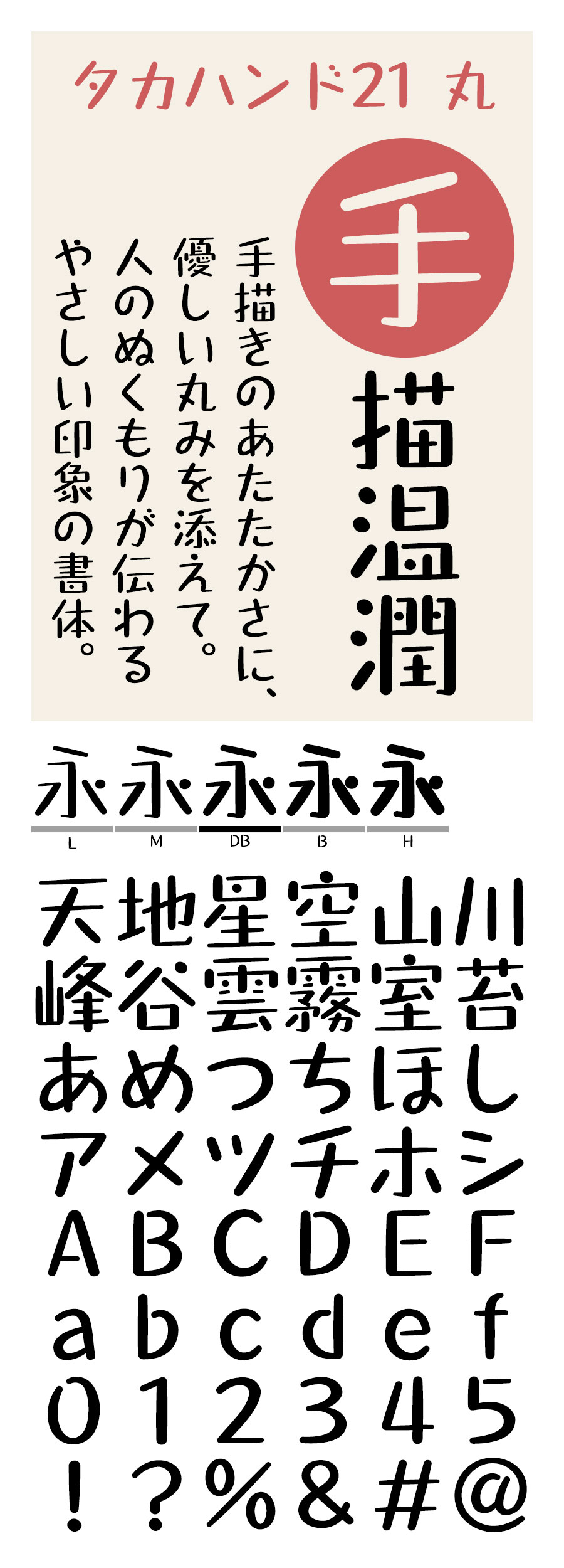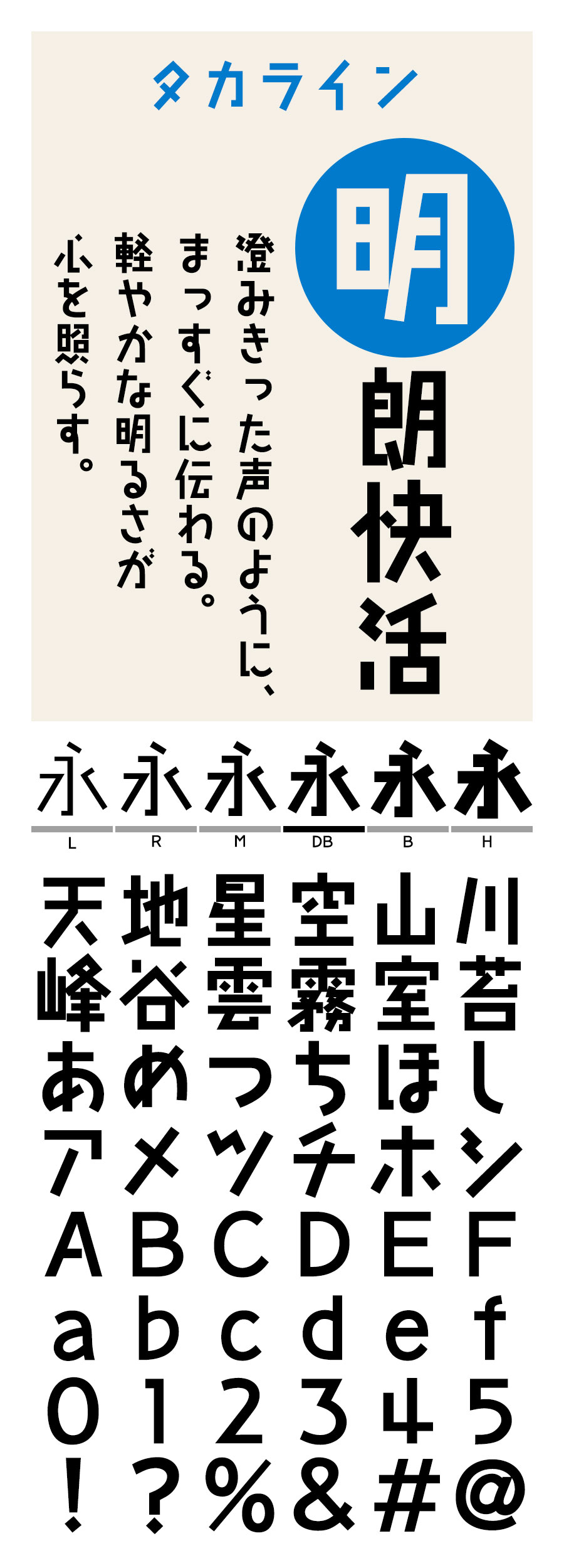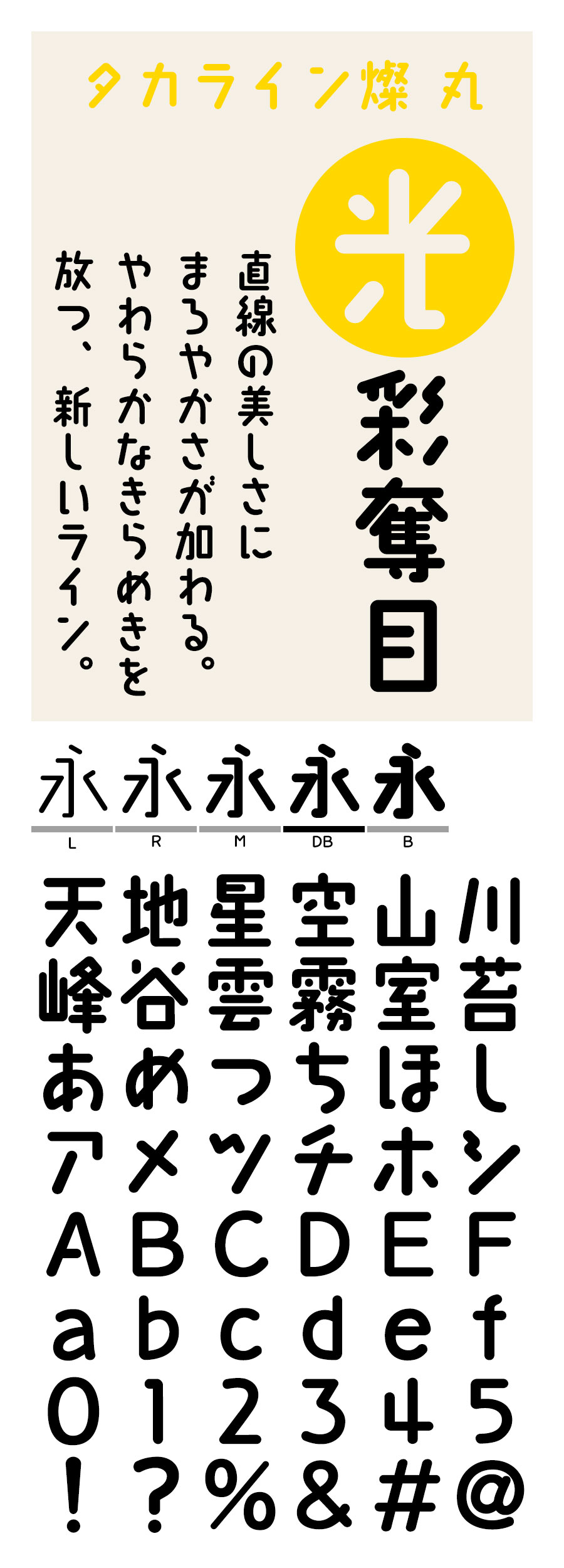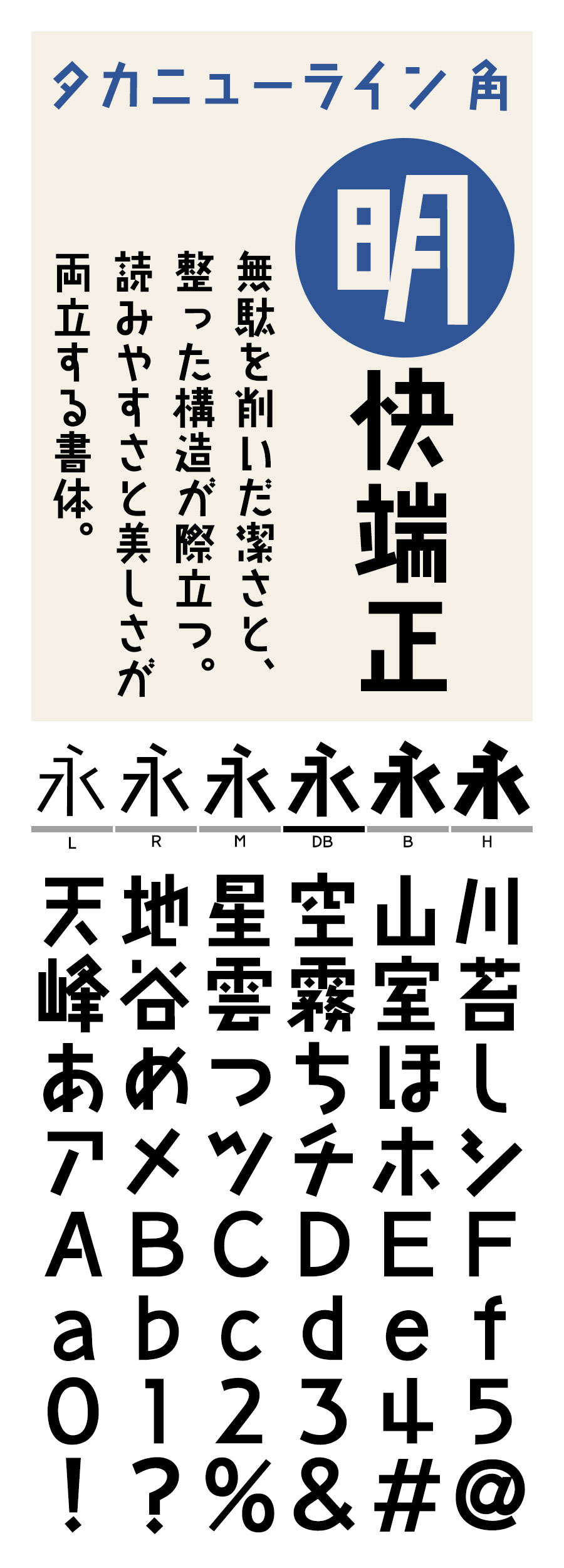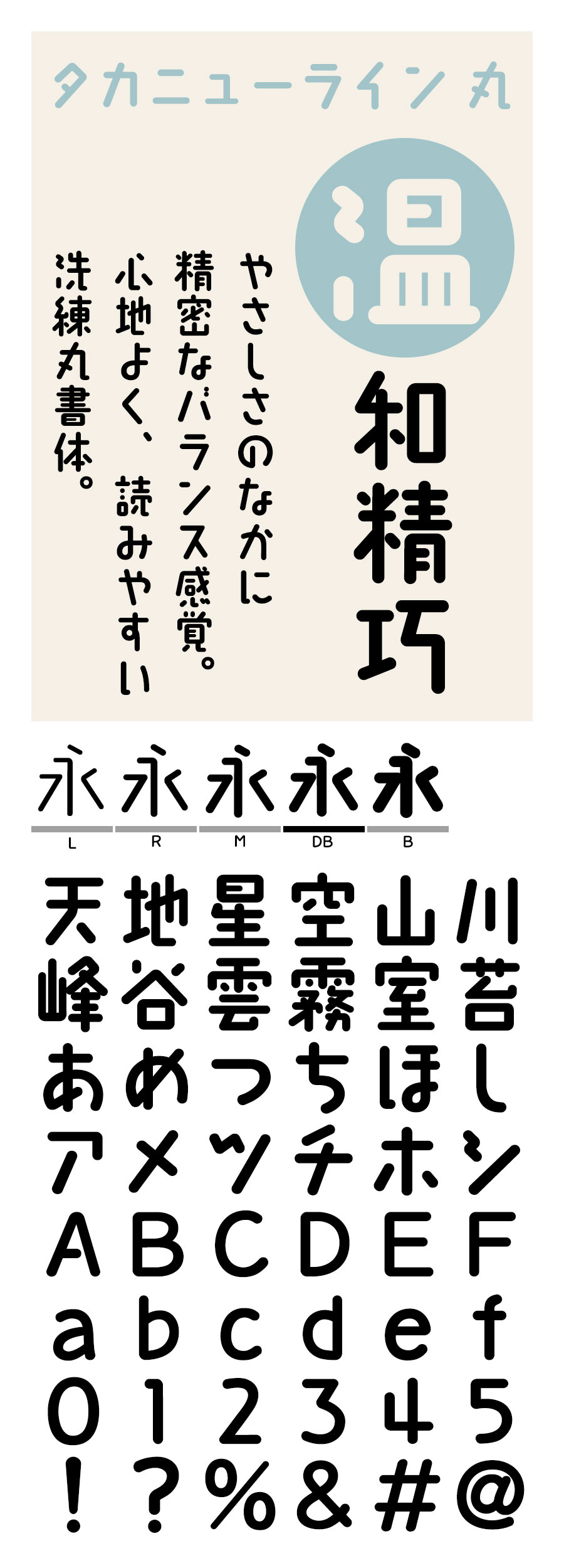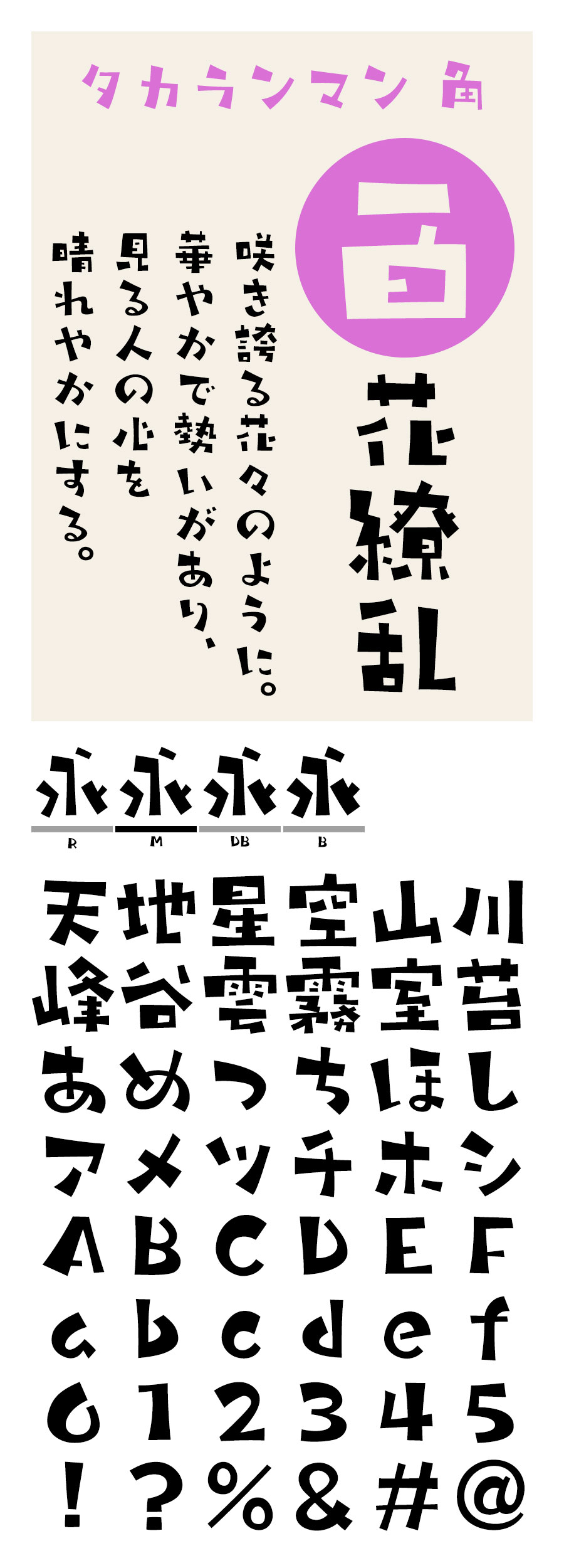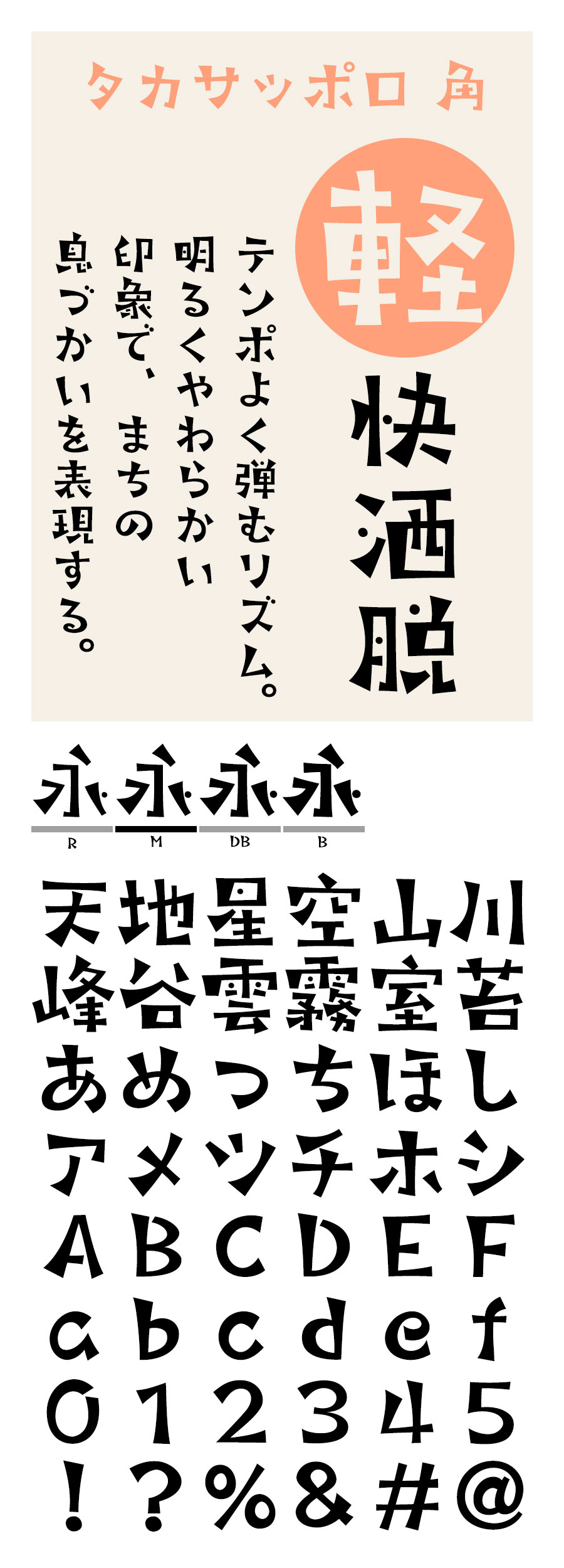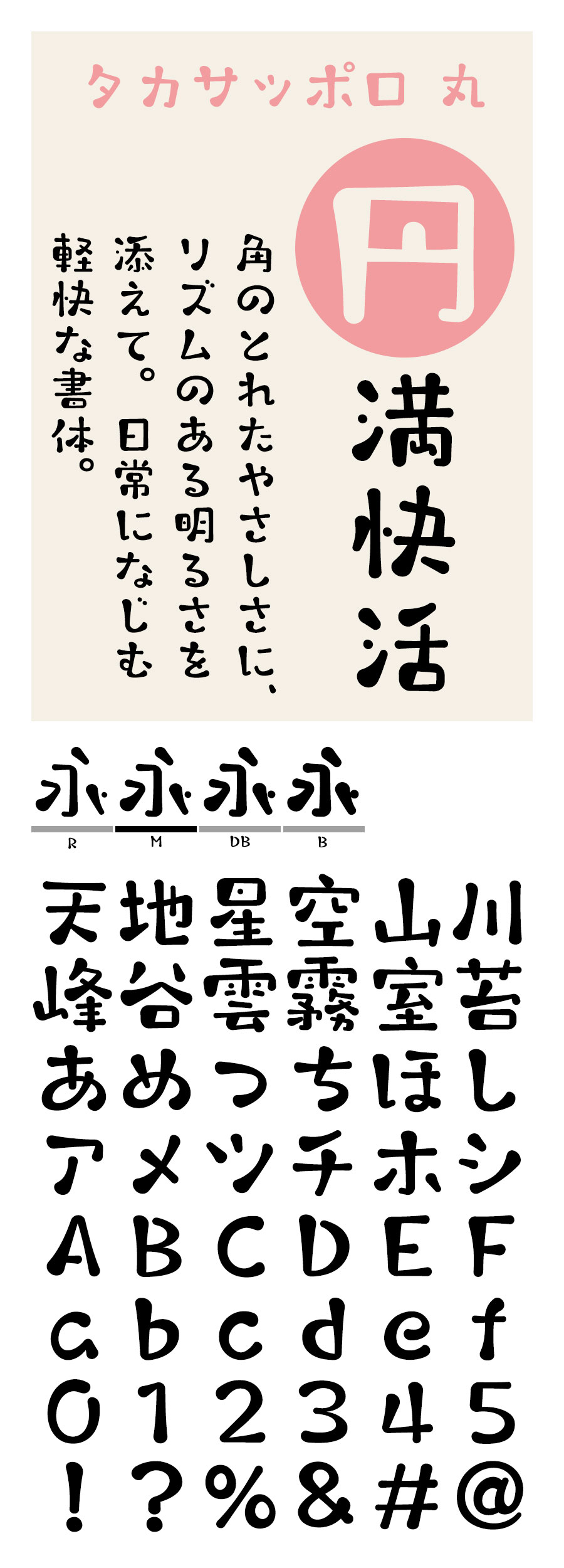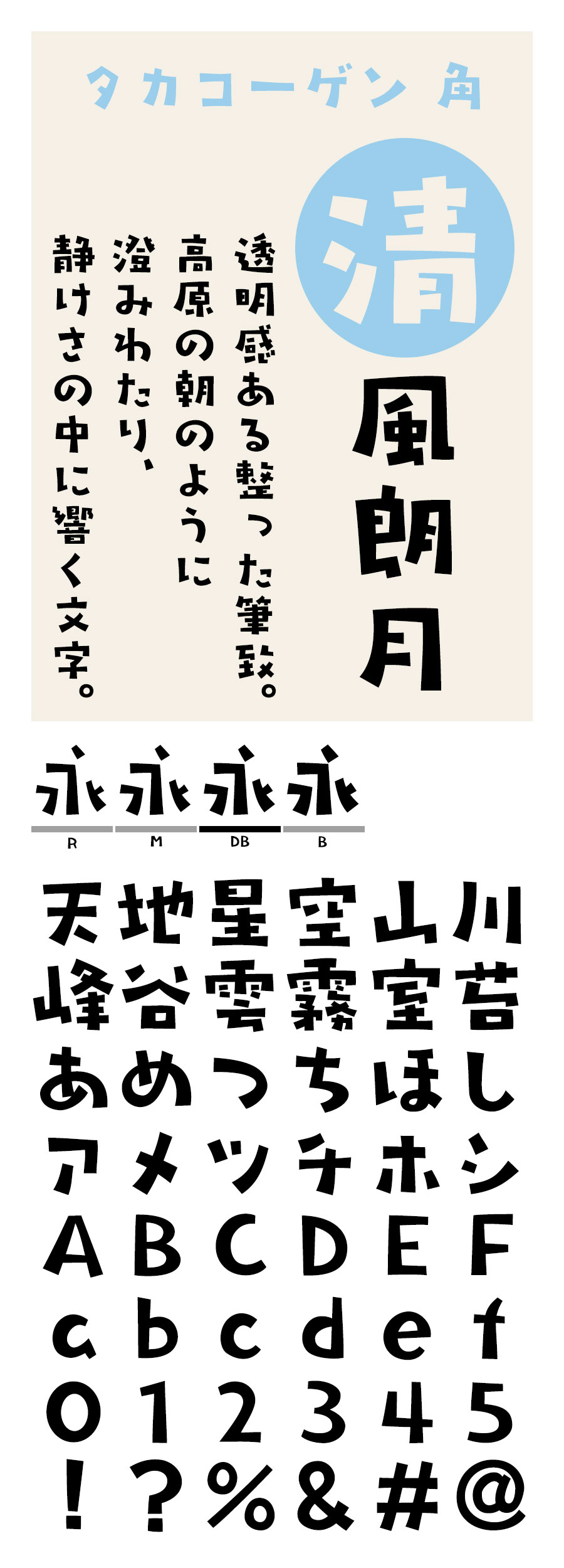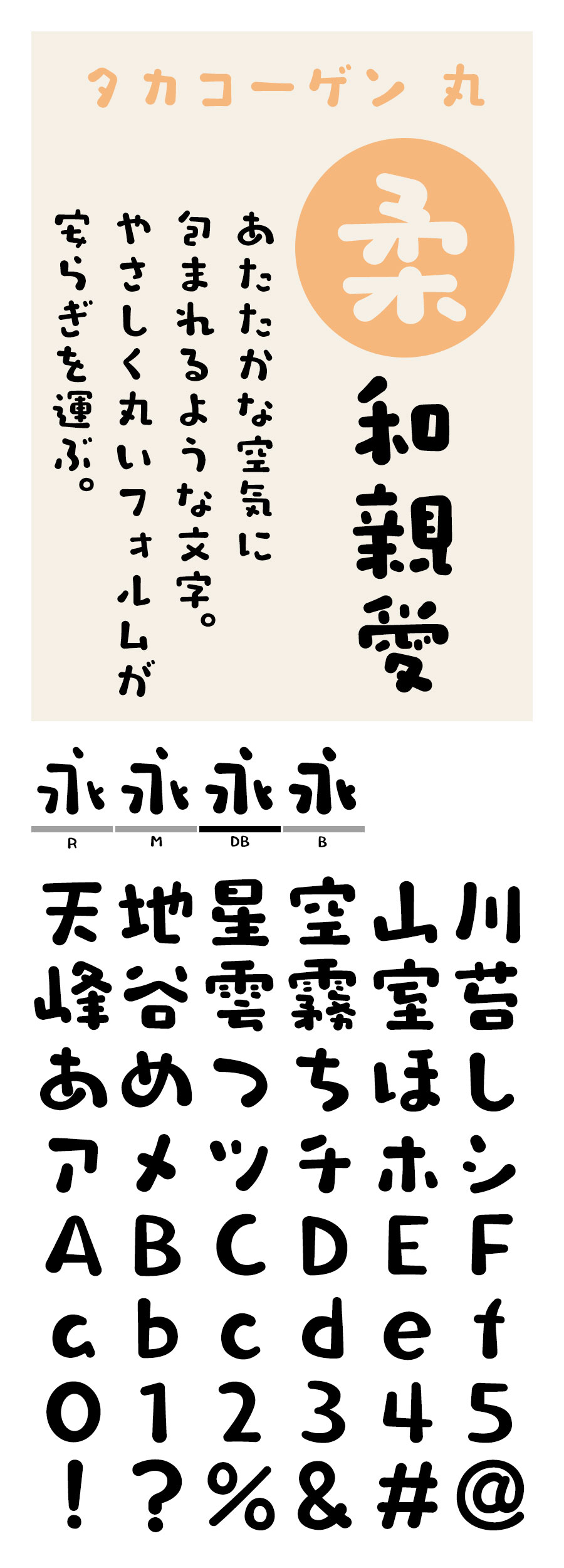
手書き風のやさしさと確かなデザイン性を備えたタカ書体は、今、誰もが使いやすい“プロの道具”として再スタートを切ります。
タカ書体とは ―― タカ書体・高原さんの軌跡
タカ書体──書体作家・高原新一が描く文字の世界。
タカ書体は、タイプ作家・高原新一氏が手がける、手書き風の温かみと親しみやすさを大切にした日本語フォントブランドです。
1987年、モリサワ社から発表された写植書体「タカハンド」にはじまり、以降30年以上にわたり、手書きの感触や柔らかなフォルムを活かした書体づくりを続けてきました。現在では50種を超える書体が、広告・出版・映像・Webなど幅広い領域で活用され、日本タイポグラフィ年鑑グランプリやニューヨークTDC展入選など、数々の賞も受賞しています。
文字に人生を賭けて――タカ書体・高原さんの軌跡
タカ書体 80年代の印刷出版業界誌に掲載される高原さん
<80年代の印刷出版業界誌に掲載される高原さん>
独学のレタリングから現場修行、そして書体の誕生と事業化へ。今回のインタビューでは、高原さんに原点、上京時代の修行、コンテスト挑戦の裏側、そして自社ブランド立ち上げに至る決断までを伺いました。
原点 — 文字に触れた最初の手応え
タカ書体 中学1年生当時に書いた漫画の模写
<中学1年生当時に書いた漫画の模写>
幼少期の模写と独学のレタリングが、のちの設計思想と観察眼を育てました。実作の成功体験が「文字を作る喜び」を確かな実感に変えていきます。
生来絵を描くのが好きで、小学生時代は皆が弁当食べてる時に、私は漫画等を自分なりにアレンジ、短縮版にした手製の紙芝居を何度か披露したものです。今でも覚えているのは“柔道の父、嘉納治五郎”です。
小学6年生あたりから、漫画の模写を夢中でやってましたが、今考える現在の文字作り土台にもなっている気がします。また中学時代、美術時間に作ったポスターが中学、高校部門で第1位となりこの辺りから、デザイナーになろうと決めました。
中学時代にはレタリングを学びたく、新聞の見出し等を切り抜き自分なりに教材らしきものを作ったりして、明朝体の漢字など1文字ずつレタリングしました。エレメントの基本みたいなものを少しは身につけ始めていた様です。
高校では3年生で『レタリング同好会』を発足。少しばかりの同好会予算で、レタリングの教材をいくつか購入しレタリングを楽しく学びました。メンバーと学校祭の立体の看板を制作。評判は最高で、先生からも大変に喜ばれました。
上京と修行と独立と挑戦 — “線”を極めて目標を定める
タカ書体 デザイン事務所で培った溝引きスキルを活かした21歳頃のレタリング
<デザイン事務所で培った溝引きスキルを活かした21歳頃のレタリング>
現場で叩き上げた版下スキルと“溝引き”の習熟が、カーブの感性を獲得。独立後はコンテスト挑戦を通じて「自分の書体を世に出す」明確な目標へ。
志望していた美大は経済事情で断念、単身上京します。入学金等を貯めるため埼玉の某工場でがむしゃらに働き、翌年には念願の日本デザインスクール(現日本デザイン専門学校)に入学。
縁があって銀座にあるデザイン会社に見習いとして働くことになり、学校は中退。主に版下作業でしたが毎日が楽しく、社長からは高原こうげんのゲンからとって、スピードのゲンちゃんと呼ばれました。そのとき道具で『溝引き』と言うのを知りました。この溝引きとは思い通りのカーブラインをキレイに引くことが出来るもので、浮世絵や美人画などの曲線を描くのにも用いられていたらしいです。そしてこれが後のあの『タカハンド』の微妙なカーブラインを自由自在に使いこなせる原点だったのです。
東京でのデザイン修行は5年間ときめていたので、北海道に戻り2年間札幌のデザイン会社の勤務し、目標通り25歳で独立します。自分には遠い世界と眺めるだけだった写研が開催していた『石井賞タイプフェイスコンテスト』に対して、これこそ挑戦しないとダメだ!と俄に意欲が湧きはじめ、この辺りからから私の大きな夢は、「自分の書体をいつの日か世に出したい」というものになりました。
第3回のコンテストに初出品するも入選出来ず、2年後の第4回のコンテストで初入選(27才)。以来、連続入選、複数点入選を続けるも目標の第1位は届かないでいました。
「タカハンド」誕生と夢の具現化 — 佳作から商品化、写植発売へ
タカ書体 タカハンドMの原字
<タカ書体 タカハンドMの原字>
受賞結果は“佳作”。それでも価値は作品そのものに宿る。逆転の電話から商品化が決まり、写植文字盤化で夢が形になります。
その頃、モリサワも同じくコンテスト開催します。1984年の『第1回モリサワ賞・国際タイプフェイスコンテスト』にディスプレイタイプ部門に出品。世界16ヶ国から202点の多くの作品が集まり、審査の結果、私の作品は佳作でした。その上に1位と2位がいるので商品化は絶対無理で、入選の喜びより佳作だったことに本当にがっかりしていました。
ところが後日かかってきた電話では、このコンテストの受賞作品の中で商品化したいのは、1位と2位のものではなく私の作品をと言うものでした。この作品が後の『タカハンド』になるのです。
その後制作に着手します。当時、私はデザイン事務所の仕事は一通り目を通しながらも、『タカハンド』の制作に集中しました。1997年完成した『タカハンドM』は写植文字盤化され発売。34才の時でした。最終的にファミリーは5書体になりました。
完成後には再びコンテストへのチャレンジを開始し、『石井賞タイプフェイスコンテスト』は第11、12、13回と入選・3位入賞、『モリサワ賞』は第2回は佳作入選、第3回は最高位の金賞不在の中、銀賞と審査員賞のW受賞を果たしました。
タカ書体 タカハンドM制作時の様子、6畳和室制作室にて
<タカハンドM制作時の様子、6畳和室制作室にて>
ロゴ・タイポアート — 書体とロゴ、教育・出版で広げた射程
タカ書体 デザイン業界紙に掲載された高原さんによる『CI』『VI』
<デザイン業界紙に掲載された高原さんによる『CI』『VI』>
タイプフェイスと並行して、ロゴ・シンボル、個展・海外展、教育・出版へと活動は拡張。社会への還元が次世代の眼差しを育てます。
28才時に大先輩に推薦いただき、日本タイポグラフィ協会の会員になります。
「タイプフェイス」はタイポグラフィの根っことも言えますが、シンボルマーク、ロゴタイプの世界もそうです。当時流行の『CI』『VI』の公募にも書体コンテストと同様、多くチャレンジ。30代がその全盛で、企業始め行政のお仕事も色々やらせてもらい、その多くは当時のロゴ・マーク集の刊行物に掲載されました。また『タイポアート』と称してタイポグラフィ作品を版画にし、個展を開いたり、タイポグラフィ協会のグループ展や海外展にも参加。その間、デザイン専門学校の非常勤講師として後輩の育成にも取り組みました。
20代の終わり頃に制作した絵文字をテーマにした本を30代半ばで自費出版し、漢字に少しでも関心を持って欲しいとの願いから北海道の全公立高校、札幌市内の全中学校に寄贈。その作品は当時の中学・高校の美術の教科書にも掲載され、今もレタリング関係の教科書に紹介されてます。
第二の柱「タカライン」 — 直線だけで“手書き感”を成立させる
タカ書体 タカライン発売当時のチラシ
<タカ書体 タカライン発売当時のチラシ>
直線のみで構成しながら、硬さを感じさせない文字。大胆な単化・省略化が、独自の読み味と評価を獲得しました。
タカハンド以降に創作した『タカラインファミリー』が発売になったのは1995年の秋。「タカハンド」とは全く異なったデザインを試みたのです。
タカ書体の原点である「手書き風」を根幹に、漢字は全文字オール直線で表現。しかし不思議にも堅さも感じさせない、個性的な魅力を放った新しい書体のひとつの方向性になりました。書き文字をベースにした大胆な字体の単化と省略化。勿論、可読の範囲でのことは言うまでもありません。これまでにない書体デザインの表現への挑戦でした。
この作品は1997年の日本タイポグラフィ年鑑の大賞に選ばれました。タカラインファミリー5書体でのことです。どちらかというと地味な世界であったこのタイプフェイス部門からの大賞作品は初めてのこと。この『タカライン』の大胆な字体の単化と省略化のデザインはその後のデザイン書体にも少なからず影響を与えた様です。
「タカ書体」は日本タイポグラフィ年鑑のタイプフェイス部門において『タカライン』の1997年以降、連続11年入選の記録と複数入選、併せて以来2024年まで最多入選22回を記録、ベストワーク賞3回、審査員賞など嬉しいことに今なお高い評価を受け続けています。
ビジネスとしてのフォントとこれから — 協業から自社ブランドへ、そして継続
タカ書体 タカハンド制作時の溝引き、筆などの仕事道具
<タカハンド制作時の溝引き、筆などの仕事道具>
ベンダー協業と自社ブランドを両輪に。制作・販売・運用を一人で切り拓き、量でなく“続ける力”で書体の裾野を広げていきます。
モリサワさんとは『タカハンド』以来、長くお付き合いを頂き、いくつかの「タカ書体」を発売頂いています。その一方で自分の作った書体が次から次へとフォント商品となって世に出すことはそう簡単ではありません。ベンダーさんへのフォント商品としての売り込みも積極的に行い、いくつかの形で「タカ書体」をフォント商品として発売することが出来ました。
そこでこの先のことを考え、思い切って『タカ書体』を自社ブランドとして確立させ、発売も自社でやろうと決めスタートしました。それが2002年、53才の時です。
当時はダウンロードよりまだパッケージが主流。2002年スタート時から現在まで書体制作はもちろん私1人でやってます。Macが嫌い、かつ苦手でマウスも1度も握ったことがなかったアナログ人間。以降の書体制作はデザインすること・書くことの他に、フォント化するためにはイヤでもMacを使わなくてはならず、これがもう1つの大きな挑戦になるのです。
日本タイポグラフィ協会の機関誌の取材を受けた際に、フォントの個人ベンダーの先駆者ですねと言われ紹介もされました。タカラインが大賞受賞の新聞社取材の折、100書体目指すと明言し記事になりました。当時の自社HPにもその100書体目指すを表記していましたが、モリサワさんへのフォントも含めると約200書体(ファミリー含)近くになっていて、そのほか仮名書体は各7ウエイトを揃え、基本67書体、総合計では469書体。通常書体と合わせると約670書体。数は余り関係ないものの、1つ1つのコツコツの積み重ねの結果です。